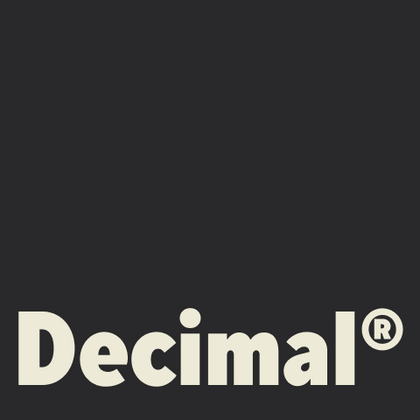
Шрифты похожие на Decimal
В коллекции TypeType представлены альтернативы, которые сохраняют четкость оригинального дизайна, дополняя его новыми возможностями. Найдите отличную замену Decimal®, сочетающую в себе техническую точность и современную эстетику, которая станет популярным выбором для цифровых интерфейсов и корпоративного дизайна. Любой шрифт из подборки, как и шрифт Decimal®, идеально подходит для проектов, где важна функциональность и читаемость: от финансовых отчетов до мобильных приложений.
Если вы устали от «заезженных» шрифтов и ищете гарнитуры, похожие на Decimal, ознакомьтесь с нашими лучшими альтернативами Decimal. Это шрифты, которые имеют близкие характеристики, но в то же время обладают новыми уникальными особенностями дизайна. Например, относятся к той же категории шрифтов, подходят для тех же целей и имеют похожие черты, но отличаются в деталях или пропорциях.
В TypeType вы найдете передовые шрифты, такие как Decimal и даже лучше: вот несколько замечательных и не столь распространенных альтернатив Decimal. Используйте этот список высококачественных, выглядящих как Decimal шрифтов, на свой вкус. Так вы сможете подобрать еще более для вашего проекта подходящий шрифт, расширив выбор, или освежить свой дизайн. Все шрифты, представленные в этой коллекции, доступны в разных форматах и по доступным ценам, поэтому вы сможете найти тот, который соответствует любым потребностям!
Найдите отличную замену Decimal и попытайтесь имитировать похожее настроение, передать нужное вам ощущение, используя его в своих проектах. Каждый шрифт, представленный на этой странице, является двойником шрифта Decimal, фактически его полным аналогом.